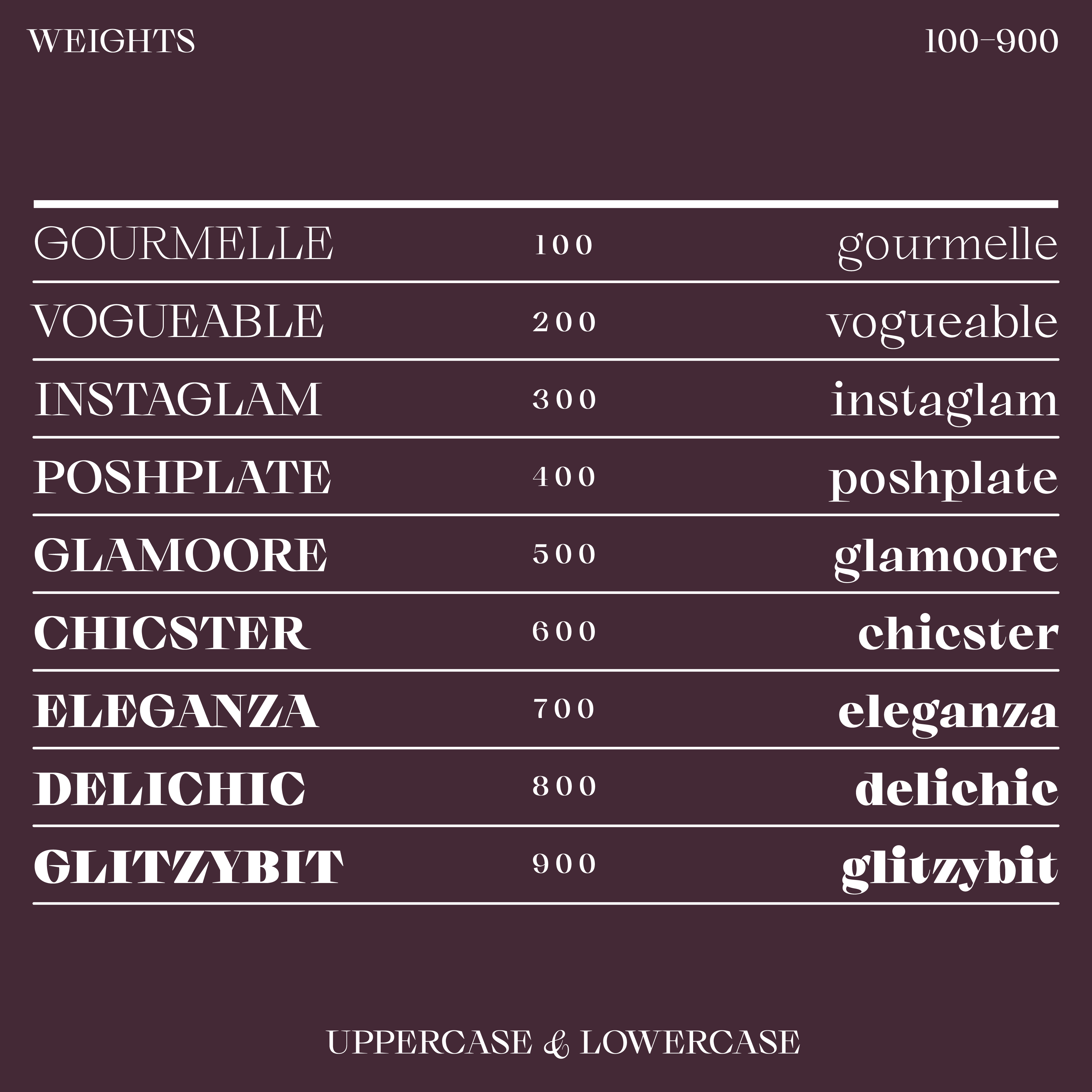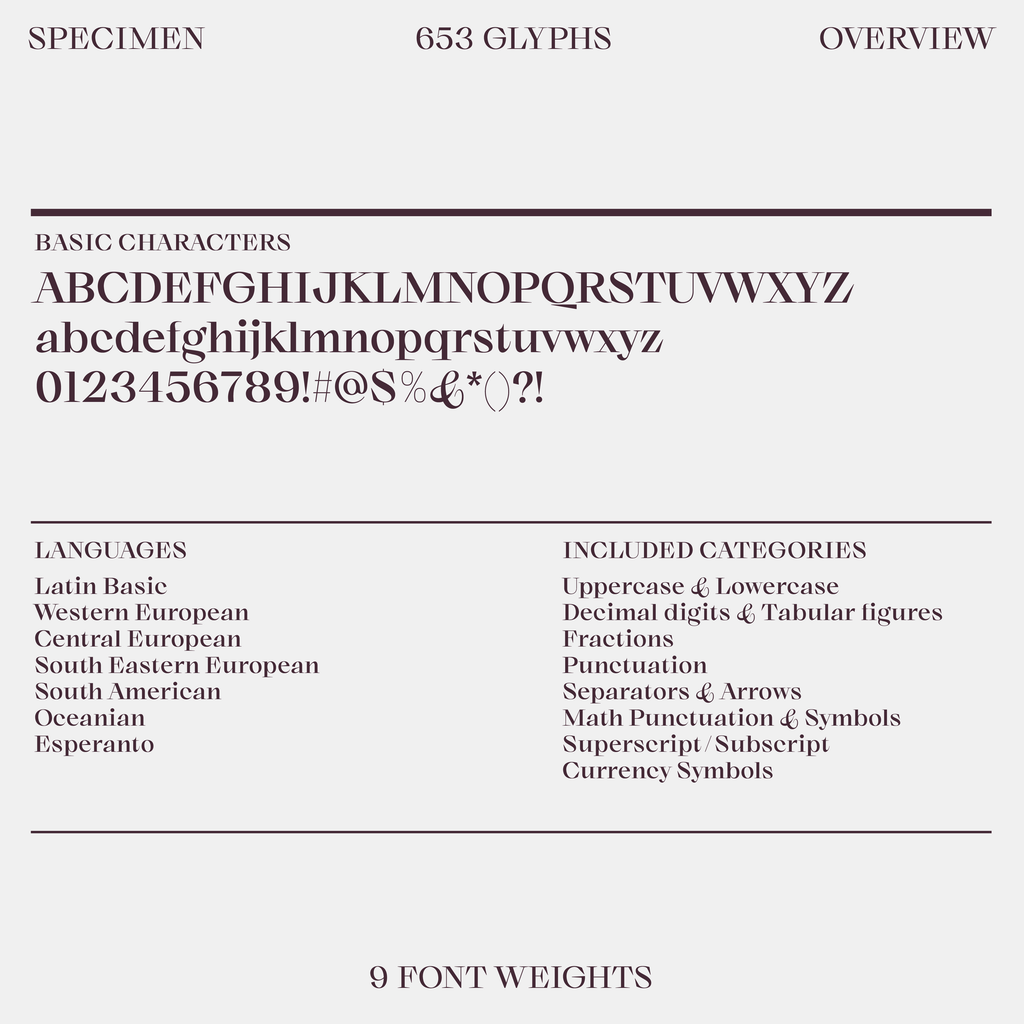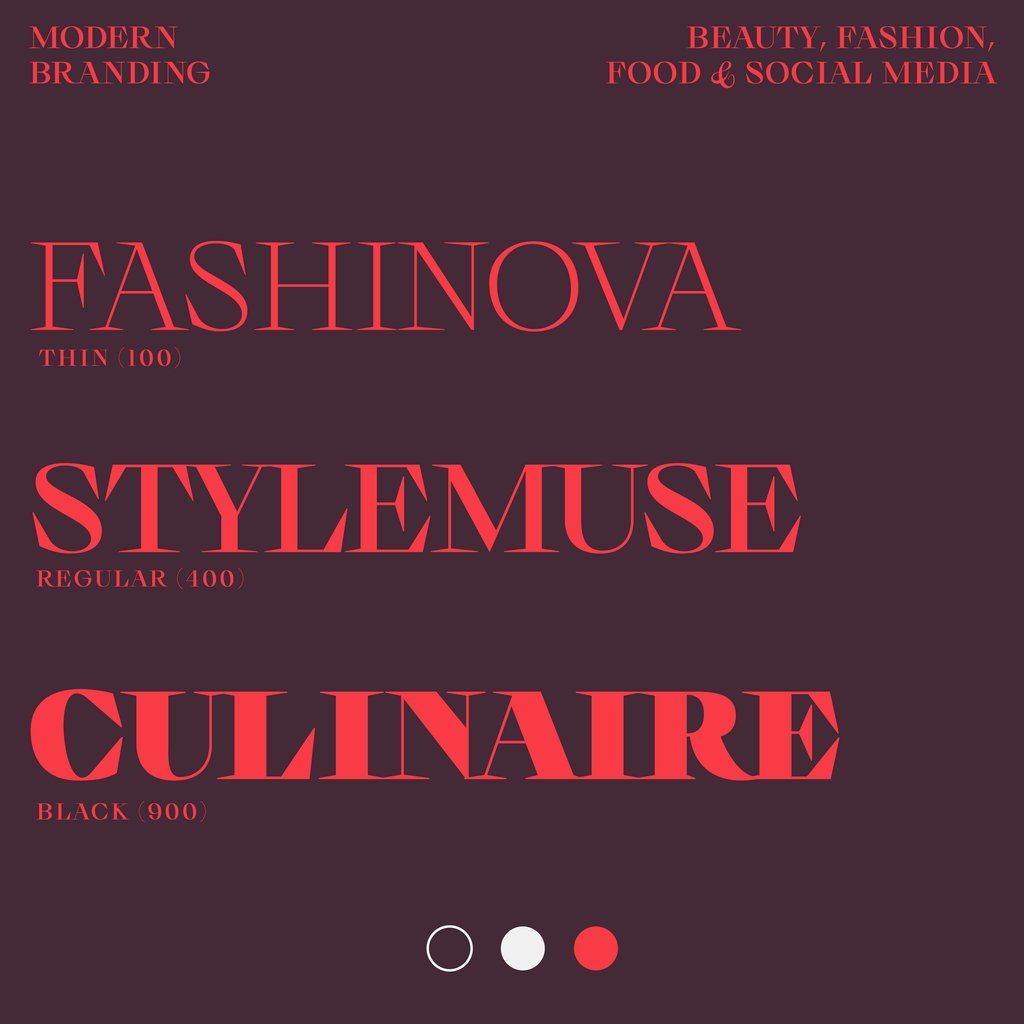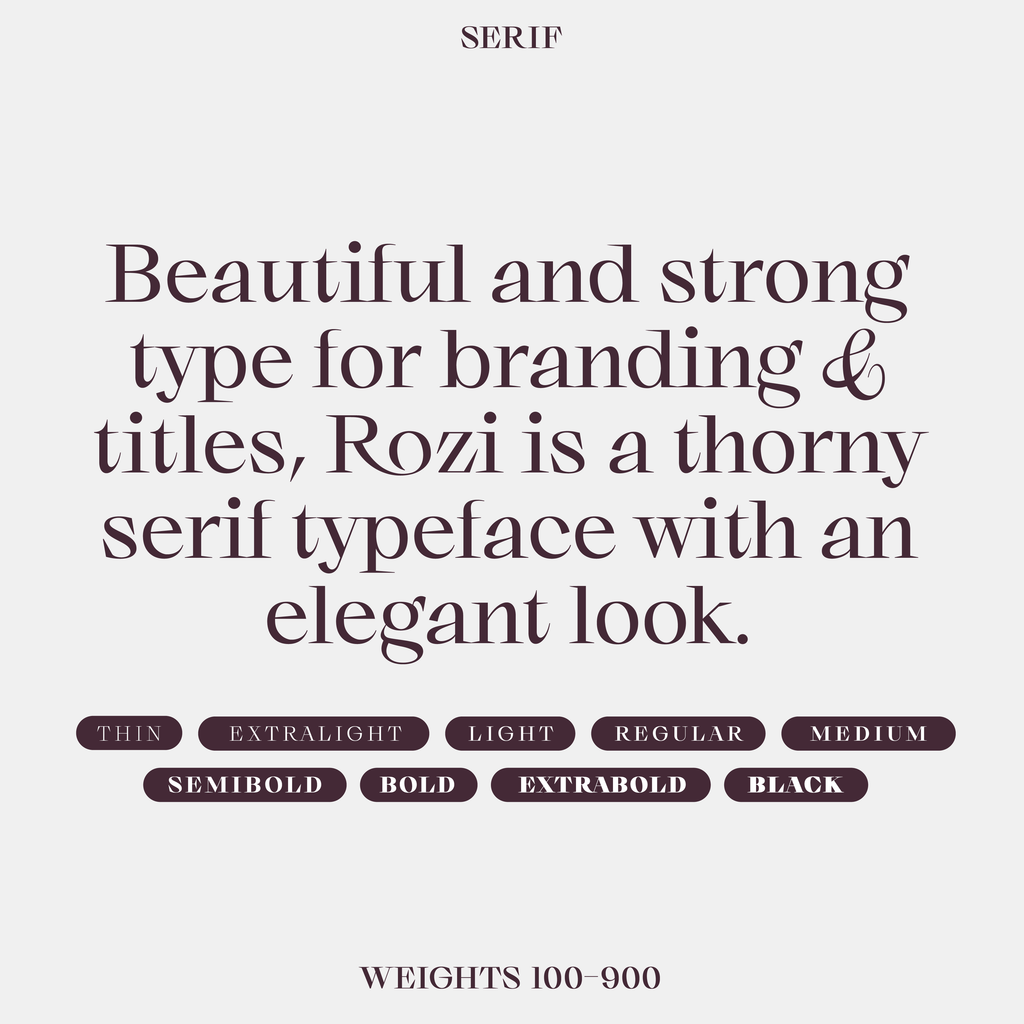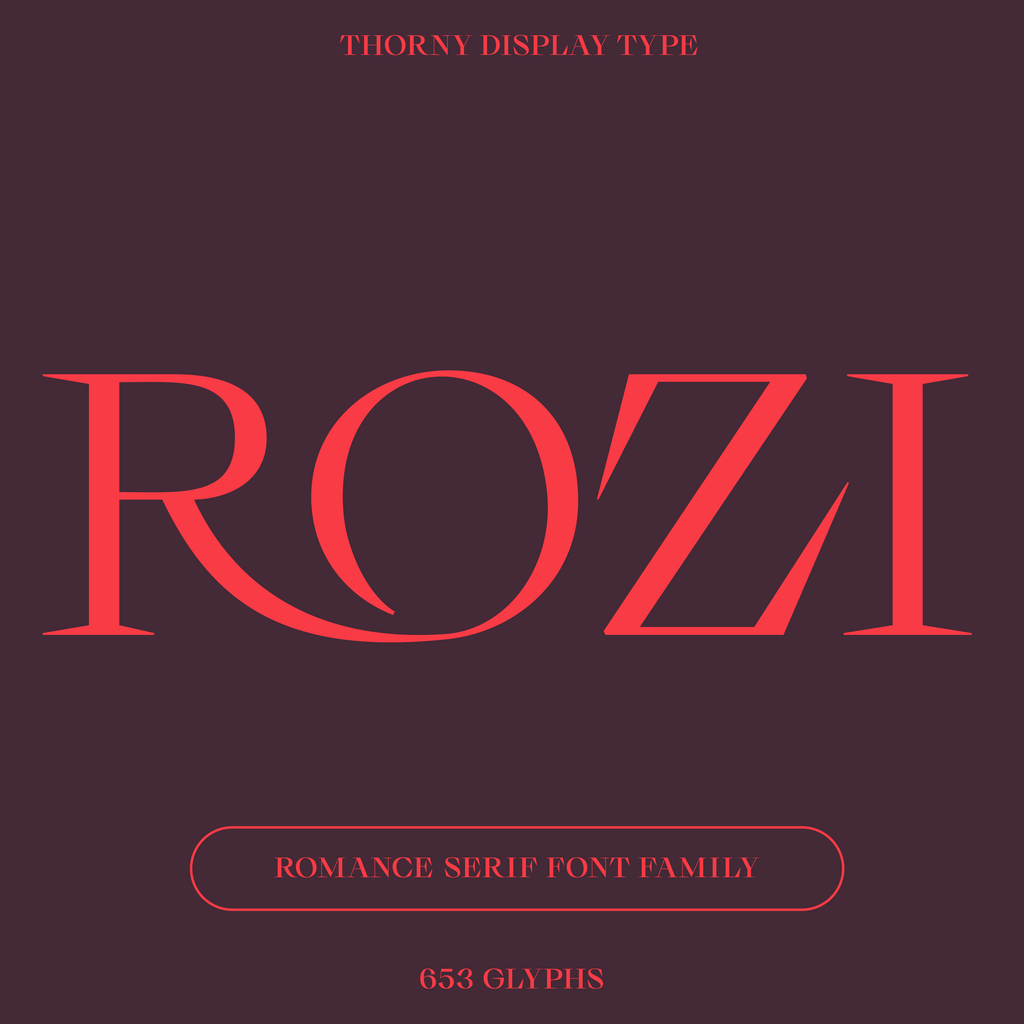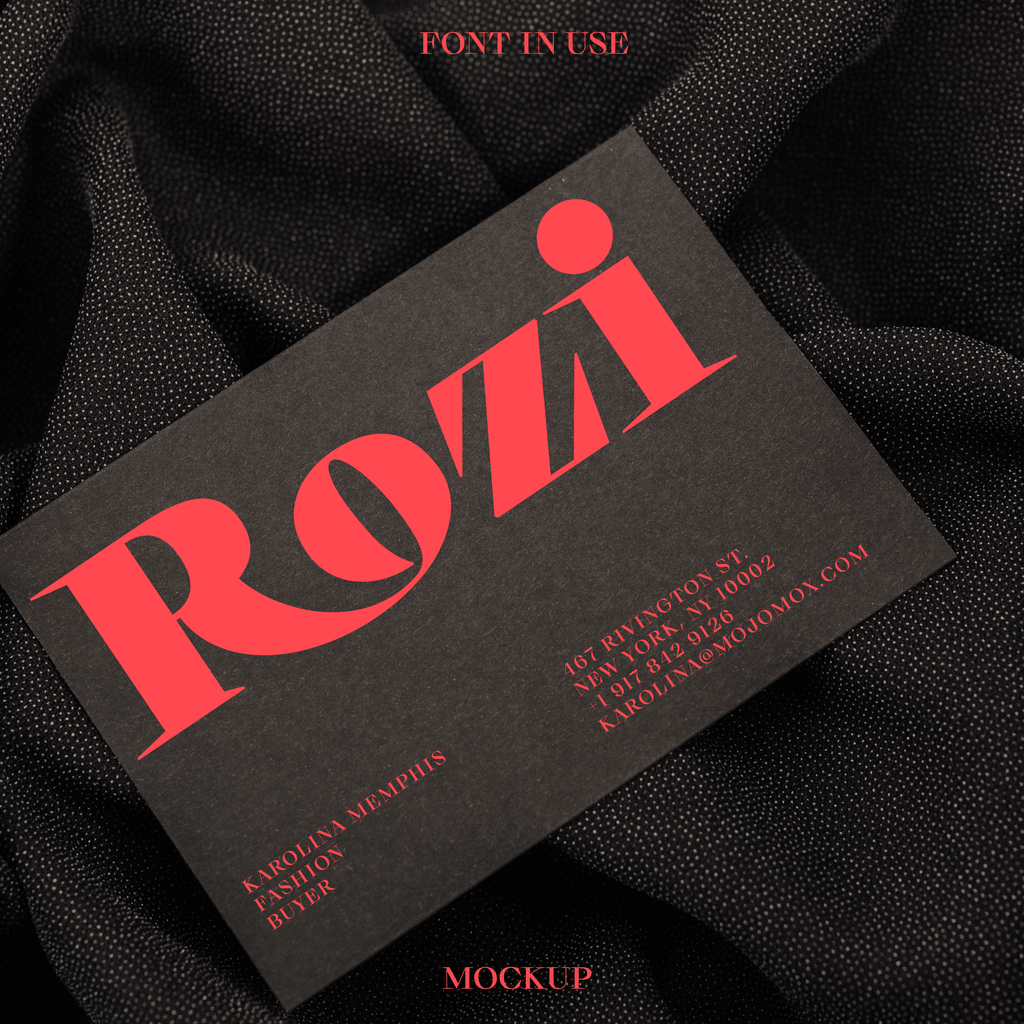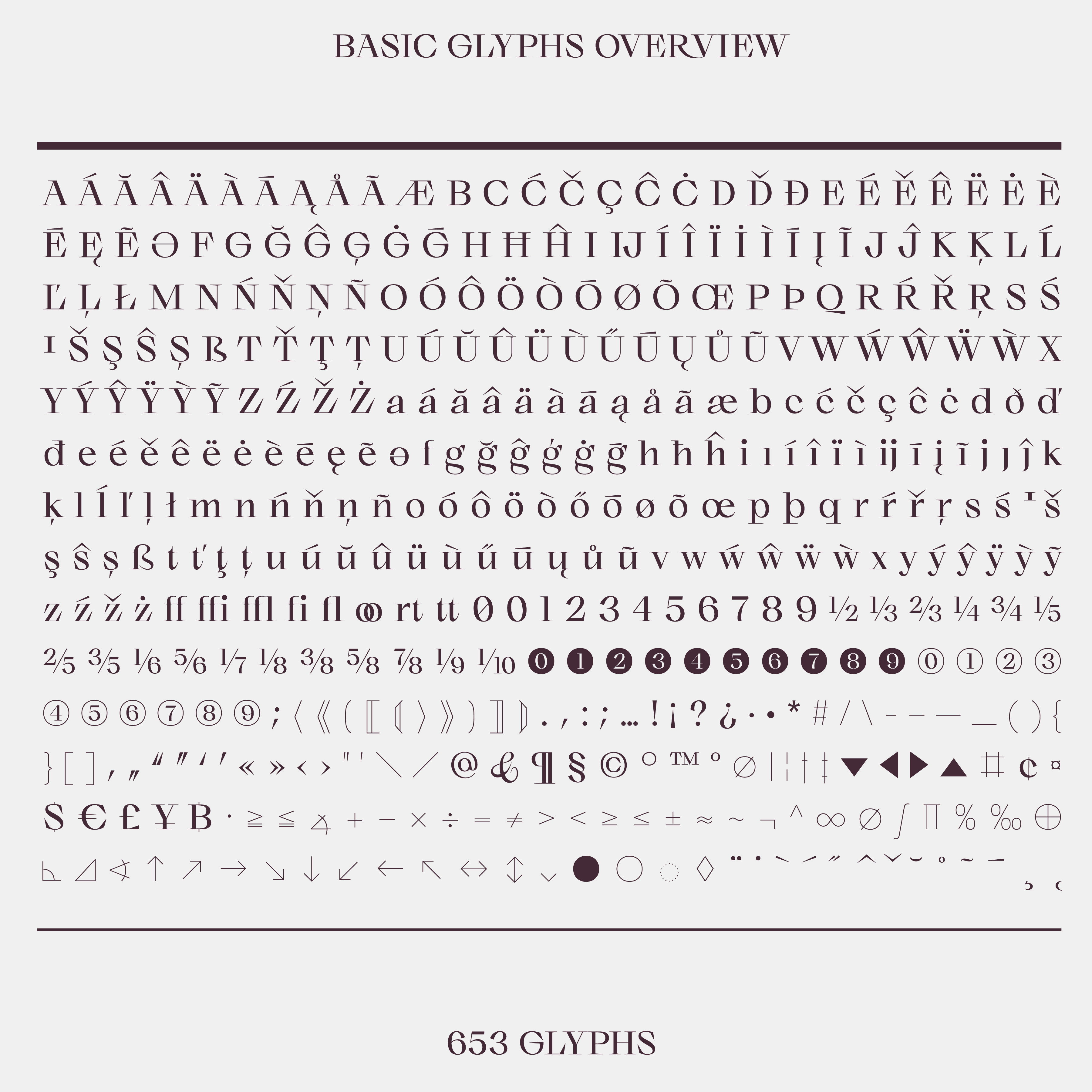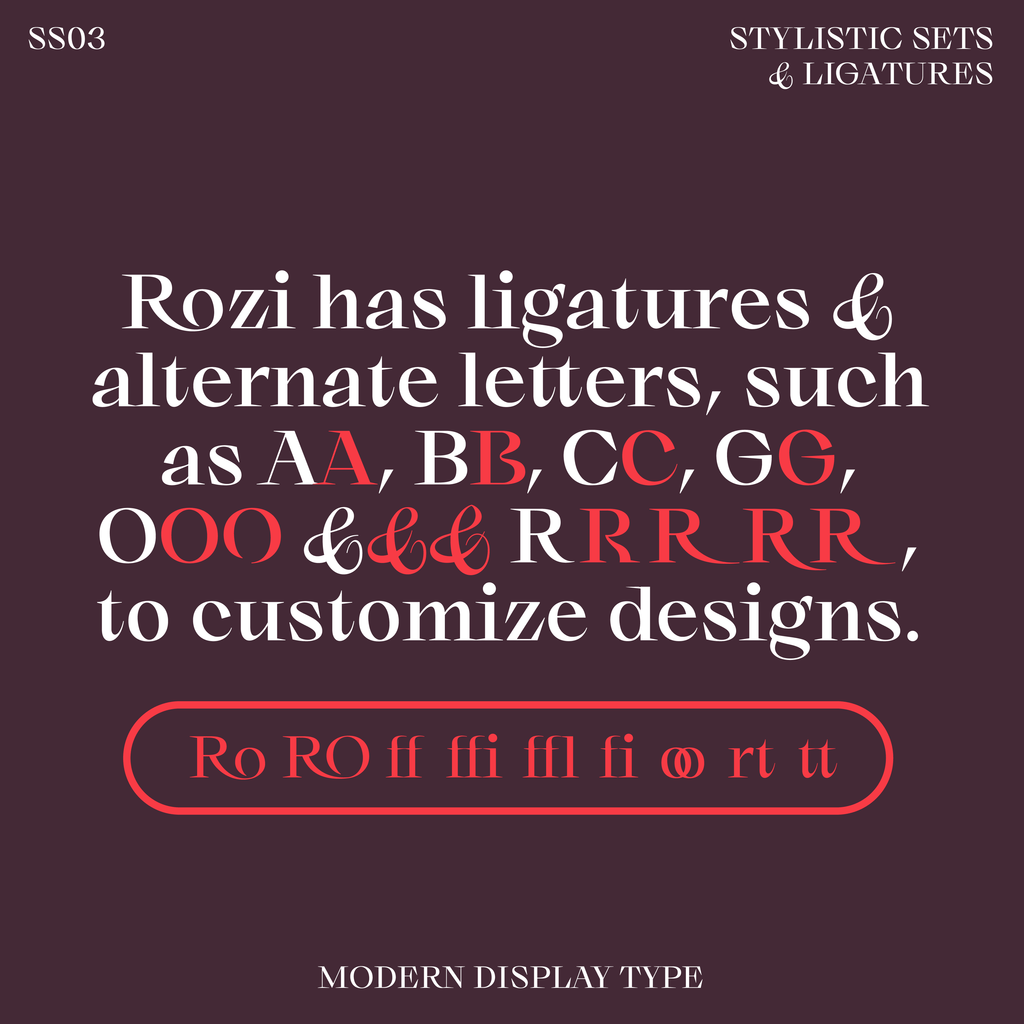
Rozi – Elegante Serifenschrift mit spitzen Serifen für Stärke
Rozi ist eine elegante und starke Schriftart für Branding und Titel. Sie ist eine scharfe Serifenschrift mit einem modernisiert nostalgischem Look in leichten und stärkeren Stilen. Rozi verfügt über Ligaturen und alternative Buchstaben, wie z. B. 2 oder mehr Optionen für die Glyphen A, B, C, G, O und R, um Designs anzupassen. Verfügbar in 9 Schriftstärken.